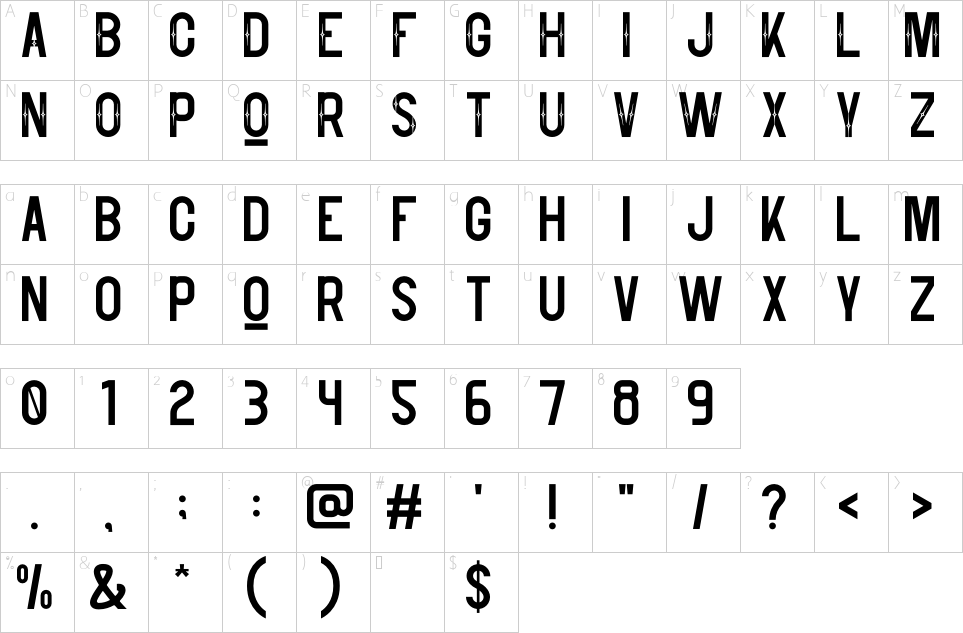
A Montelgo Sans Serif é uma fonte elegante e moderna, perfeita para criar design gráfico impactante. Com um design simples e moderno, ela se destaca no ambiente digital, oferecendo uma mistura harmônica de elegância e simplicidade. Esta fonte foi criada por Jada Akbal e, embora não possamos saber todas as inspirações e influências por trás do design, é um testemunho do talento que Jada Akbal possui. Com sua utilização fácil em ambientes Windows e Mac, Montelgo Sans Serif pode ser uma escolha ótima para designers e profissionais de design que buscam uma fonte sem serif que oferece uma sensação moderna e contemporânea. A Fonte Montelgo Sans Serif foi baixada 1.995 vezes, o que sugere seu grande potencial e popularidade, e continua a ser um recurso valioso para aqueles que buscam estilos de fontes modernos e elegantes.